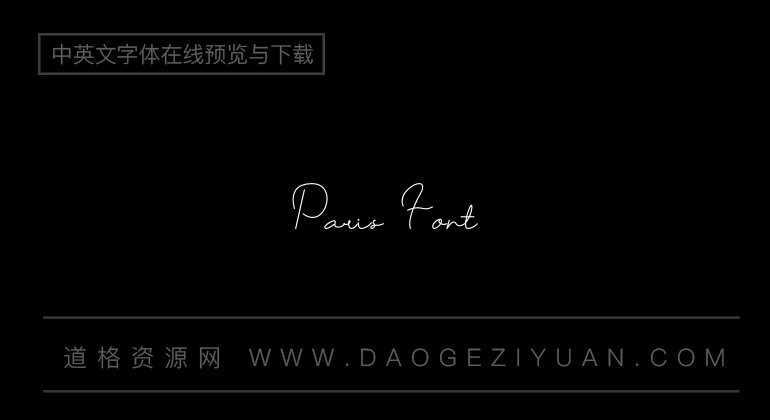
Paris Font 是一种优雅且时尚的手写字体,适用于多种设计场景。该字体由 Frenchfoundry 制作,具有流畅的连字和独特的笔画。它适用于品牌标志、标题和海报等场合,也适用于印刷品和数字设计。该字体具有多种字重和风格,例如正常、粗体和斜体。此外,它还包括大写字母、小写字母、数字和标点符号等全套字符。 Paris Font 的设计灵感来自于巴黎的风情和文化,具有浪漫和优雅的特点。内容介绍
Paris Font是一款非常不错的手写艺术字体,具有很好的视觉感,适合于文化类的宣传设计、商业类品牌的广告和产品包装设计以及个性化文字排版等较多场景。